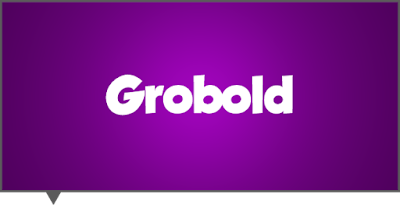
خط Grobold خط جميل ، حيت أنه بسيط ، و سبق أن استعملناه في درس ” درس 35 : كيفية رسم خط يذوب شوكولاته بإستعمال illustrator + ملف Vector ” ، يمكنك تحميل هذا خط من رابط أسفله …